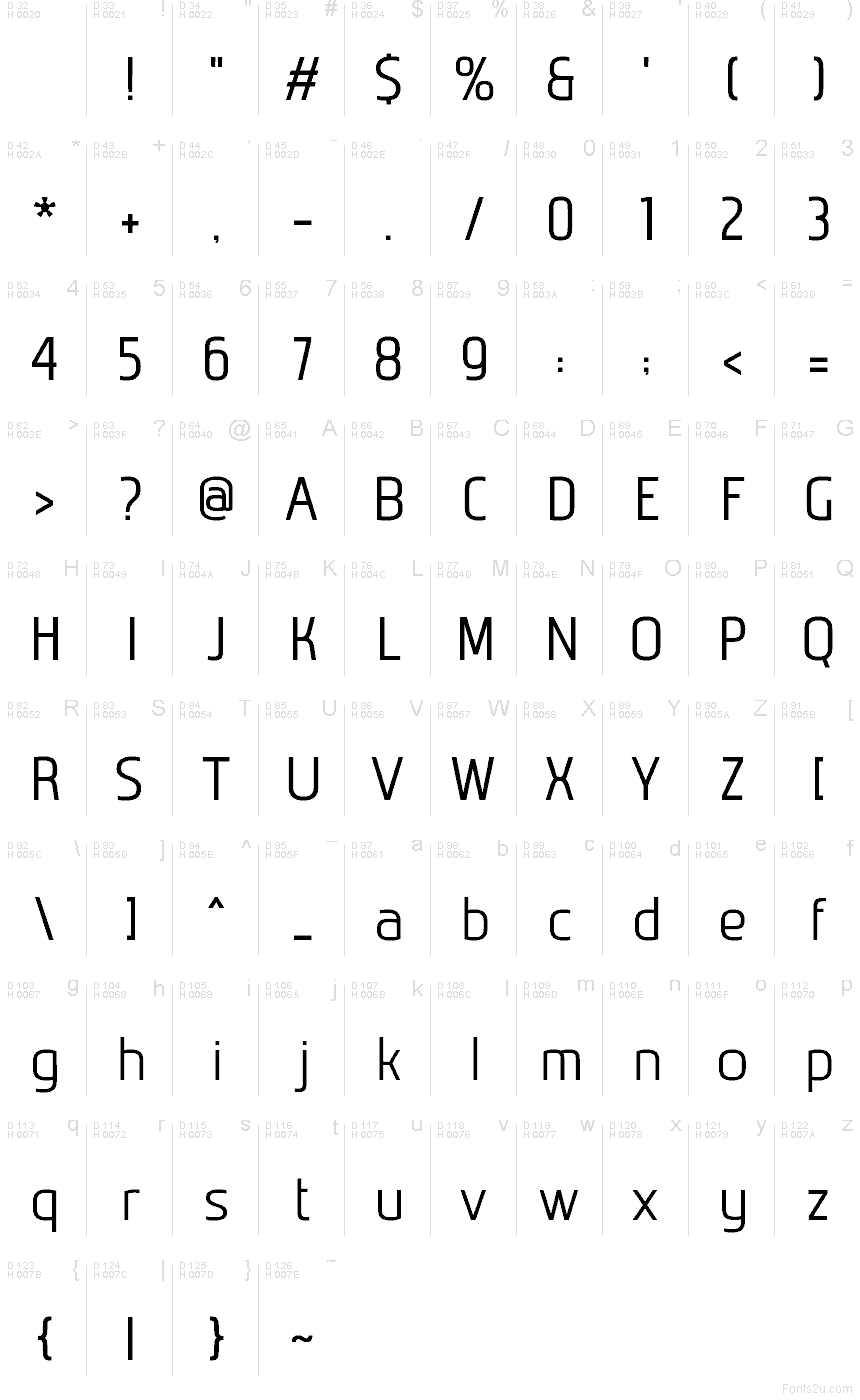
Ukážka písma Emirates Essentials Thin
Emirates Essentials Thin od štúdia Glyphminds Studios je bezplatné, tenké bezpätkové písmo s pokojným, súčasným nádychom. Písmená využívajú dlhé, čisté vertikály a široké zaoblené krivky, čo písmu dodáva ľahký, vzdušný rytmus, ktorý pôsobí viac ako moderný branding než ako prísna geometria.
Prirodzene zapadne do módneho brandingu, wellness obalov, hotelových materiálov, úvodných obrazoviek aplikácií či redakčných titulkov, kde vďaka priestranným tvarom udržuje striedmu a exkluzívnu atmosféru. Keďže ide o bezplatné písmo, výborne sa hodí aj na krátke nadpisy a monogramy, pretože tenké ťahy a otvorené krivky pôsobia aj v krátkych slovách premyslene a čisto.